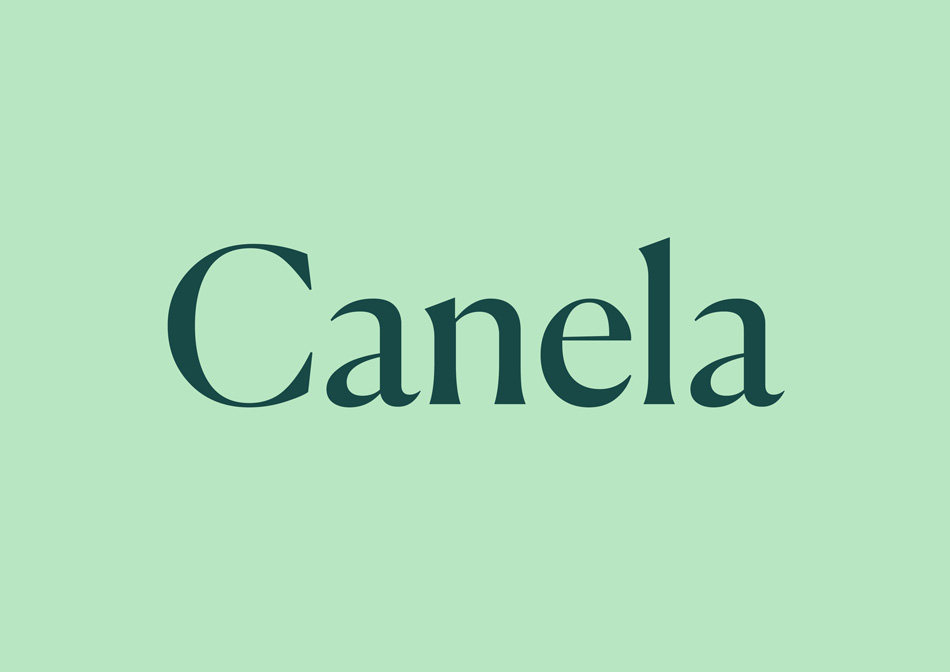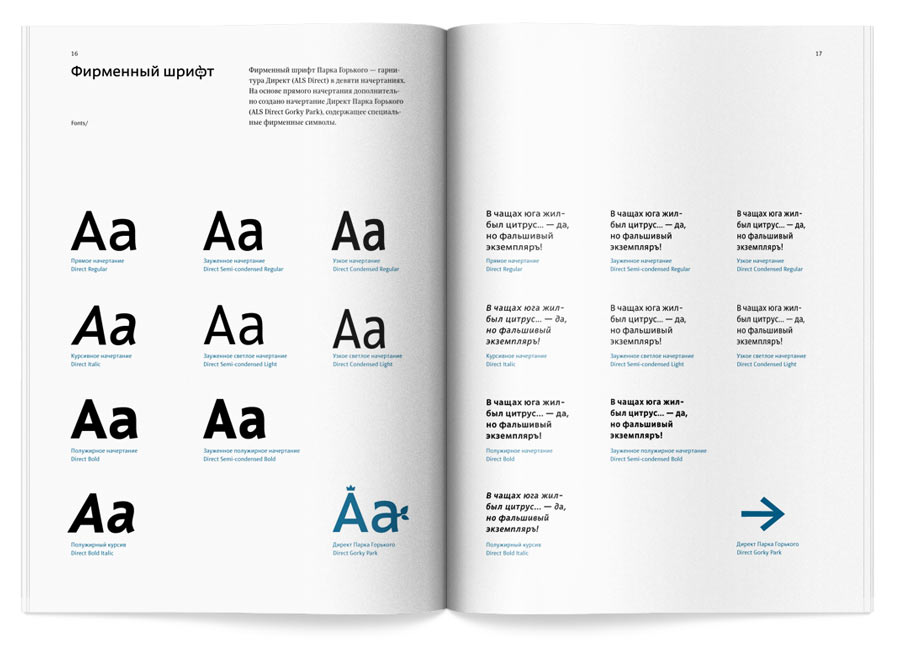
6 советов, которые помогут вам выбрать правильную типографику для дизайна логотипа
Эффектная типографика — один из важнейших факторов успешного дизайна логотипа. Каждый шрифт имеет свою индивидуальность и по-особому впечатляет. Правильно подобранный шрифт — это ценность и голос вашего бренда, тогда как неправильный шрифт может оттолкнуть вашу целевую аудиторию.
Итак, имея сотни тысяч шрифтов, как узнать, какой из них подходит для вашего логотипа и какой шрифт стоит выбрать? В этой статье мы поделимся шестью основными советами, которые помогут выбрать шрифт для вашего бренда для того, чтобы вы могли подобрать правильную типографику для своего логотипа.
1. Разбиритесь в основах
Прежде чем создавать логотип, включающий типографику, важно понимать основы типографики. То есть понимать различные типы шрифтов (с засечками, без засечек, рукописные, моноширинные, акцидентные), основы композиции, иерархи, принципы масштаба, а также такие понятия, как кернинг и высота строки.
Если вам пока некомфортно разрабатывать собственную шрифтовую надпись, то подобрать правильный шрифт для дизайна логотипа будет непросто. Если вы новичок в типографике, найдите время, чтобы изучить, как она используется в логотипах и в общем контенте. Проанализируйте, как различные шрифты те или иные эмоции, их масштаб, иерархию на странице и как эти вещи влияют на общее восприятие контента.
Когда вы будете готовы погрузиться в разработку шрифта своего логотипа, ознакомьтесь с другими логотипами в вашей отрасли и не только, а также с тем, как они используют шрифты. Найдите для себя избранные логотипы, они могут быть вам отличным источником вдохновения при проектировании собственного проекта.
2. Думайте о своей аудитории
Знание ожиданий вашей аудитории является ключевым к созданию словесного знака или любого другого логотипа. Если ваша аудитория ожидает определенного внешнего вида от вашего бренда (или вашей отрасли в целом), вам необходимо убедиться, что любой созданный вами логотип соответствует этим ожиданиям.
Если вы разрабатываете логотип для нового бренда, вам необходимо принять во внимание ценности вашего бренда и то, что ваша идеальная аудитория может ожидать от бренда с такими ценностями. Если ваш бренд, например, должен быть одет с иголочки и вы захотите использовать шрифты, которые создают такое впечатление в вашем логотипе, избегайте чего-то традиционного, например Baskerville или Caslon. Однако, если ваша аудитория состоит из клиентов из отраслей с более традиционными ценностями (банки, юридические фирмы и т.д.), современный логотип может и не подойти.
При разработке логотипа для ребрендинга вам нужно проявлять особую осторожность, чтобы не оттолкнуть текущих клиентов.
Есть много известных случаев, когда новый логотип вызвал негативную реакцию потребителей (редизайн логотипа Gap в 2010 году — один из самых печально известных случаев, когда компания отказалась от нового дизайна всего через неделю). Рассматривайте постепенные изменения, а не полностью новый дизайн.
3. Не гонитесь за трендами
Логотипы должны проходить испытание временем. Это означает, что вам следует избегать модных шрифтов. Шрифт, который сегодня кажется передовым, рискует выглядеть устаревшим через полгода или год, что может привести к очередному редизайну.
Шрифт, который сегодня кажется передовым, рискует выглядеть устаревшим через полгода или год.
Когда словесный знак или логотип создается без учета тенденций, его можно использовать десятилетиями. Рассмотрим логотип Jeep. Он используется с 1963 года, и хотя значок в логотипе немного изменился с годами, слово «Jeep» осталось неизменным. Это более чем 50 лет использования!
Исключение из правил может быть тогда, когда вам нужно разработать логотип который будет использоваться только временно (например, для мероприятия), и когда логотип должен указывать на определенный момент времени.
Если это так, то смело используйте модный шрифт, который сразу будет распознаваться как принадлежащий определенной эпохе.
4. Чем проще, тем лучше
Логотипы обычно используются в различных размерах. Поскольку некоторые из этих размеров могут быть довольно маленькими, чем проще, тем лучше. Вам нужно создать логотип, который хорошо масштабируется и может использоваться везде, где это необходимо, без необходимости переработки дизайна.
Это не означает, что ваш логотип обязательно должен быть минималистичным. Но использование принципов минимализма, таких как удаление всего ненужного, — это надежный подход к дизайну логотипа.
При выборе шрифтов для логотипа, не выбирайте сложных и замудренных. Шрифты с большим количеством мелких деталей не будут хорошо смотреться при маленьком размере, и важные детали могут быть потеряны.
Это также относится к количеству шрифтов, которые вы можете использовать в своем логотипе. В большинстве случаев вам нужно выбрать один шрифт, хотя, если ваш слоган также будет частью логотипа, для него можно выбрать другой шрифт.
Если вы все же собираетесь более одного шрифта в вашем логотипе, убедитесь, что вы следуете типографским принципам комбинирования шрифтов.
7. Аматик СК и Жозефин Санс
Amatic SC — это нарисованный от руки веб-шрифт, идеально подходящий для художественного использования. Это несложный выбор, если вам нужен шрифт, выходящий за рамки корпоративного стиля. Шрифт может выделять заголовки или некоторые фрагменты основного текста. Тем не менее, это лучше всего работает только для заголовков.
Затем пригласите Жозефин Санс, чтобы завершить эту стильную комбинацию в слогане или основном тексте.